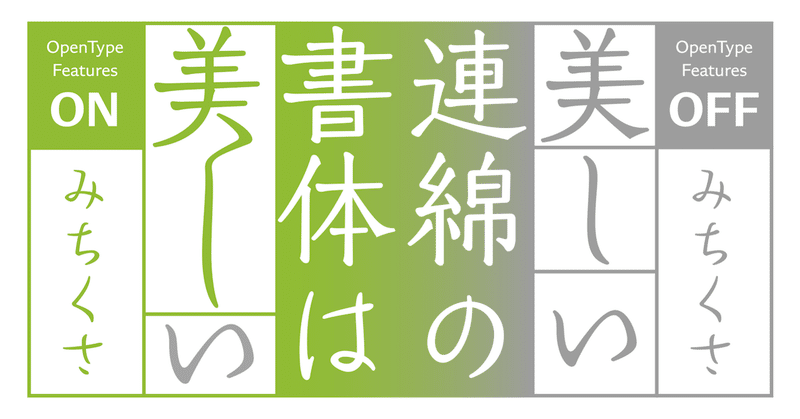
筆のまにまに。言葉によって形が変わるフォント「みちくさ」
今回は「みちくさ」という書体についてご紹介したいと思います。
「みちくさ」は、フォントに内包されている “ある機能” を活用することで、言葉や文章に合わせて自動的に形が変化するユニークな書体です。
1. 「みちくさ」とは
まずはデザインのお話から。
「みちくさ」は2017年にリリースした明朝体風のデザイン書体です。
高い重心に、ふところを絞った骨格と、やわらかく現代的なエレメントが特徴的です。
ふところ、重心
「ふところ」は、縦画と横画が構成している内側の空間のことを指します。ふところが広い書体はおおらかな印象、狭い書体はひきしまった印象を与えます。
それに対して「重心」は、文字のバランスの中心のポジションのことです。一般的には高めであれば緊張感や品格を生み、低めなら安定感や親しみやすさを感じさせると言われています。
・独創的でやわらかな「かな」
「みちくさ」のひらがなは、従来の明朝体にみられる活字由来のフォルムも取り入れつつ、新しいデザインにチャレンジしています。ペンで手書きしたような、なめらかに流れる運筆を採用することで、優しくユニークなデザインになっています。
また、カタカナは深くしなやかなカーブが特徴で、おおらかでエレガントな表情を持っています。
・かなに寄り添う明朝体テイストの「漢字」
漢字は明朝体のテイストを取り入れつつも、縦横の太さの差を抑え、かなに合わせてやさしい雰囲気に仕上げています。また、明朝体特有の「うろこ」をとることで、ハライなどの滑らかで美しい曲線を際立たせ、かなとの親和性を高めています。
・オールドスタイルの進化系
「みちくさ」は重心が高く、ふところを引き締めた作風で、「オールドスタイル」というジャンルに属します。
書体のスタイルは「モダンスタイル 」と「オールドスタイル」の大きく2つに分けることができます。「モダンスタイル」は幾何学的に整理されたクリアなデザインであるのに対し、「オールドスタイル」は有機的な筆跡で情緒のあるデザインになっています。
「みちくさ」は、シンプルで柔らかなエレメントや、活字の系譜に捉われないかなを採用することで、従来のオールドスタイル書体にはない特徴を持ち合わせています。
ここ数年はオールドスタイルの書体が使われているシーンをよく目にしますが、その中でも特にユニークな表情をもつ書体です。
2. 言葉によって形が変わるフォント
・連綿体の和文フォント
ここまで「みちくさ」のデザインについてお話ししてきましたが、この書体の最大の特徴は、なんといっても連綿体のかなが搭載されていることです。
「連綿体」とは、日本では平安時代の書物を起源とした続け字で書いた書体のことを指します。欧文では「スクリプト体」と呼ばれる手書きの筆跡のを活かした書体ジャンルに相当します。
欧文書体においては、連綿字形を持つフォントは広く普及しています。
例えばfとiの合字(リガチャ)や代替字形(オルタネート)、スクリプト体などで文字と文字が連綿しているデザインを見かけたことのある方も多いのではないでしょうか?
しかし、このような機能を積極的に取り入れた和文書体はあまり例がありません。
和文書体で連綿機能があまり搭載されてこなかった理由はいくつかありますが、大きな課題の一つとして 、縦書きの日本語の連綿体は文字の組み合わせによってつながる位置が異なり、規則的に連綿させることが難しいということがあげられます。
技術を駆使してその壁を乗り越え、さらに新しい試みを取り入れて発展させたのが「みちくさ」のプロジェクトでした。
実際に連綿合字や代替字形を使って組んでみるとこのように…
文字が繋がったり、同じ字でも言葉によって代替字形が出てくるといったところがこのフォントの面白いポイントです。
・言葉によって形が変わるフォント
「みちくさ」は「OpenTypeフォント」という現在主流のフォントファイルの規格に基づいて制作されており、フォントに内包されているプログラム「OpenType機能」を活用することで縦組みをした際にただ連綿化するのではなく、文脈を考慮した連綿体や合字を呼び出す仕組みを実現しました。それによって、単調な文字組みではなく、手書きのような自由な動きを表現することができるのです。
OpenType機能
高度で美しい組版を実現するための機能です。特定の文字の間のスペースを調整することで美しい字送りを自動的に実現するための情報や、文章の前後関係を解釈して組版に適した代替字形等を呼び出す情報などが搭載されています。
「みちくさ」は和文書体において最もポピュラーな9354字を搭載する文字セット(Adobe-Japan1-3)に加えて、1000文字を超える連綿体や代替字形を搭載しており、例えば下の画像のように「も」だけでも4種類の形があるのです…!
さらに、実はかなだけではなく、「美しい」など数は多くありませんが漢字から連綿する連綿合字や代替字形が存在します。
(筆者の推しリガチャは「すしリガ」。抱き字が攻めてて良い…!)
百聞は一見に如かず!
実際に文字を打つ過程を見ていただくと、言葉の前後関係によって字形が変わっていることをお分かりいただけるかと思います。
「みちくさ」の開発で最も大変だったのが、この文脈によって字形が変わる機能の設計と動作検証です。
まず、文章の中でも文頭や文末で文字が入力された時のみで連綿化するものや、ある特定の単語でのみ連綿化するもの、といった条件を設定しました。
それに合わせた連綿合字や代替字形をデザインした後、実際に様々な文章を入力してテストを行い、デザインの改定作業やどれくらいの頻度で言葉の形が変わるかを検証していきました。
これらの工夫によって文章を組んだ時にバランスよく連綿体が発動するようになっているため、「みちくさ」は見出しからキャプションほどの文章組みまで幅広く使うことができます。
最後に、InDesignやIllustratorなどの組版・グラフィック制作ソフトでの動作確認を経て、「みちくさ」はOpenType機能を活用した様々な表現が可能な和文フォントとして誕生したのです。
デフォルトではベタ組み(文字詰めや連綿字形が入ってない状態)で、正方形を意識して設計されているため、もちろん横組みでも違和感なく使うことができます。
4. 開発ウラ話
最後に、「みちくさ」の開発ウラ話をお届けします。
・コンペティションから生まれた書体
「みちくさ」は、2014年に行われた「モリサワ タイプデザインコンペティション」という、世界中から新しいアイデアの書体デザインを募るアワードにエントリーされた書体でした。実は「みちくさ」は最終選考に残ったものの、惜しくも入賞をのがした作品でしたが、他にないユニークなデザインや仕様のからくりの魅力から開発に至りました。「みちくさ」のように、入賞作品以外の書体にも全て目を通し、新しいタイプデザインの発掘と創造に力をいれています。
この画像は、コンペティション応募時と、製品としてリリースされた「みちくさ」の比較画像です。並べてみると、当初のものからデザインが変更されていることをお分かりいただけるかと思います。
「みちくさ」に限らず、応募作品から採用させていただき製品化される書体は、開発をスタートする際に具体的な使用想定やその書体のデザインの強みについて作者と一緒に協議し、デザインの改定を繰り返して完成させていきます。
書体名は原作者であるデザイナーさんによって「猫の道草のように気まぐれで奔放な書体」だから「みちくさ」と名付けられ、応募時のままリリースされました。書体名の由来を聞くと、「美しい字」という印象だけでなく、気ままで自由な書体としてなんだか親近感が湧きますよね。
豊富な字形バリエーションのかなというコンセプトや連綿化の基準も、原作者自身が長文の活字を読むことが苦手であることから、本文に音とリズムを与えることをテーマに書体を制作したという点に基づいています。書道における連綿体のルールよりも、組んだ時のバランスや音のつながりを表現したというところが、この書体にどこかユニークさを感じる理由かもしれません。
みなさんも「みちくさ」が街中でどんな場面で使われているか探したり、文章中でどこが連綿して、どんなリガチャが出てくるか、実際に使って試してみてください!